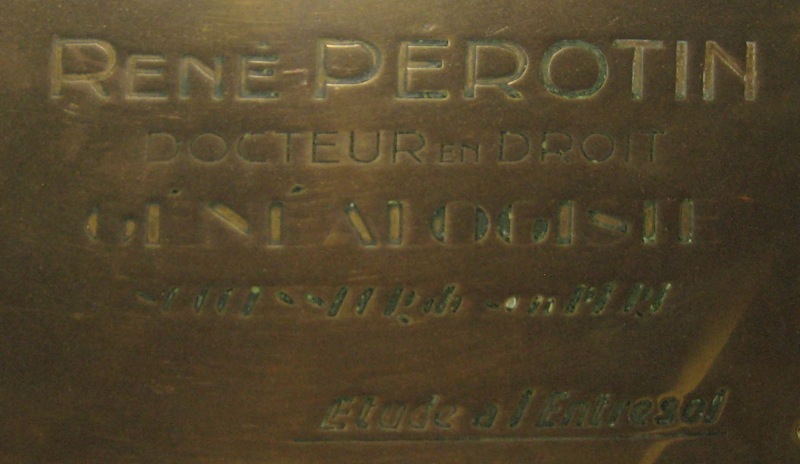
Bonjour Typo, Je recherche sans succès quelle police des années 20 (?) a été employée pour une plaque, et si la fonte numérique correspondante existe (avec les petites caps). J’ai placé une photo de cette plaque là : http://telure.free.fr/plaque.jpg Mes recherches sur des mots clés du genre « art déco » me renvoient des tas de réponses tarabiscotées, mais jamais rien que se rapproche de cette linéale, datée mais sobre. Merci de vos lumières... F.P.